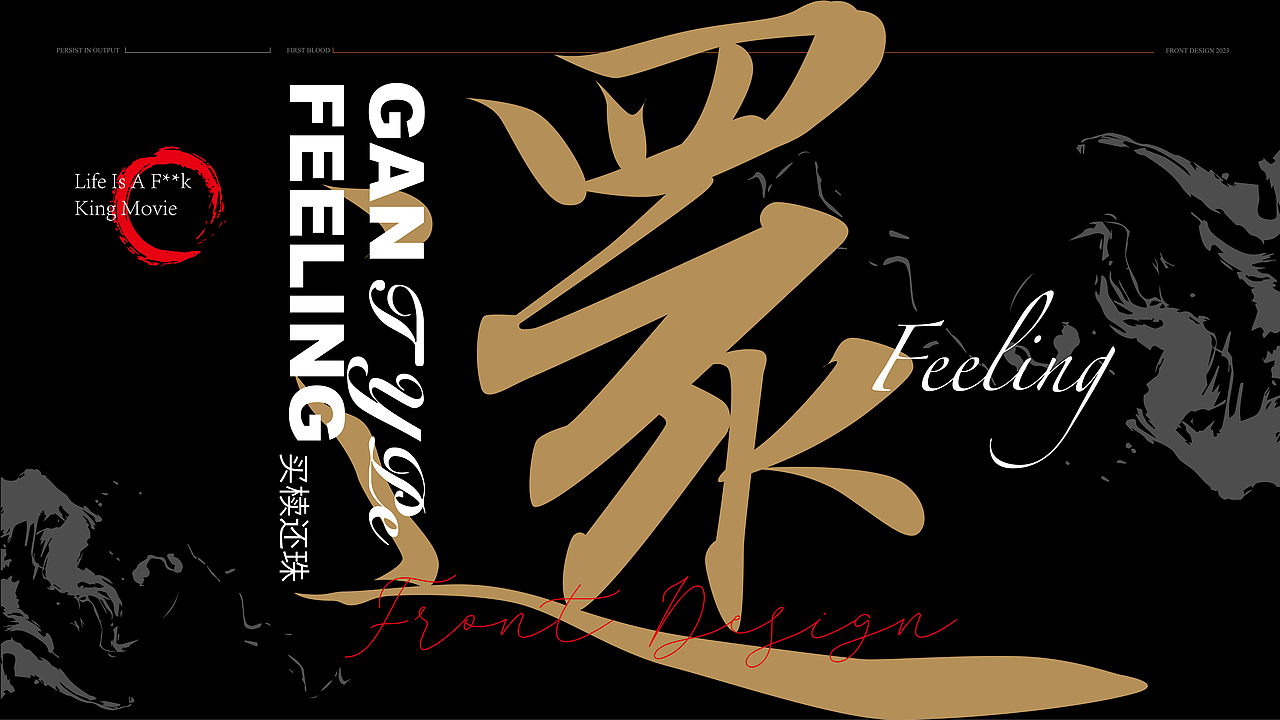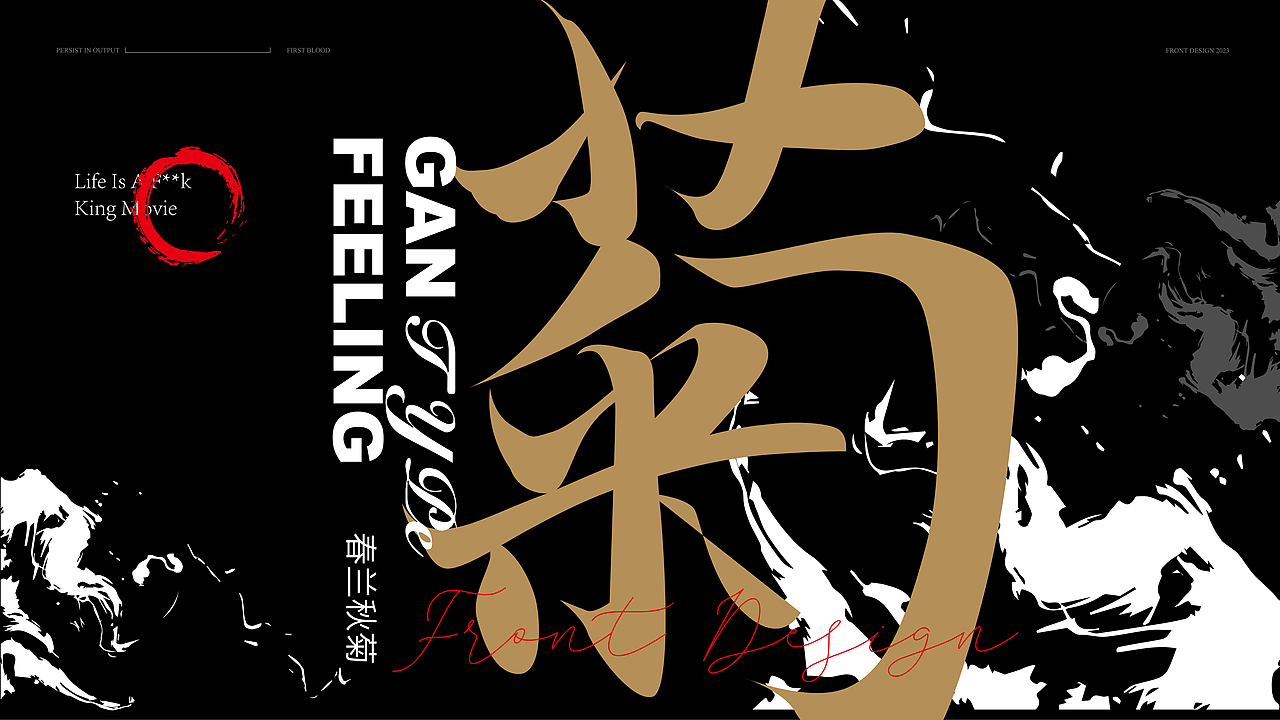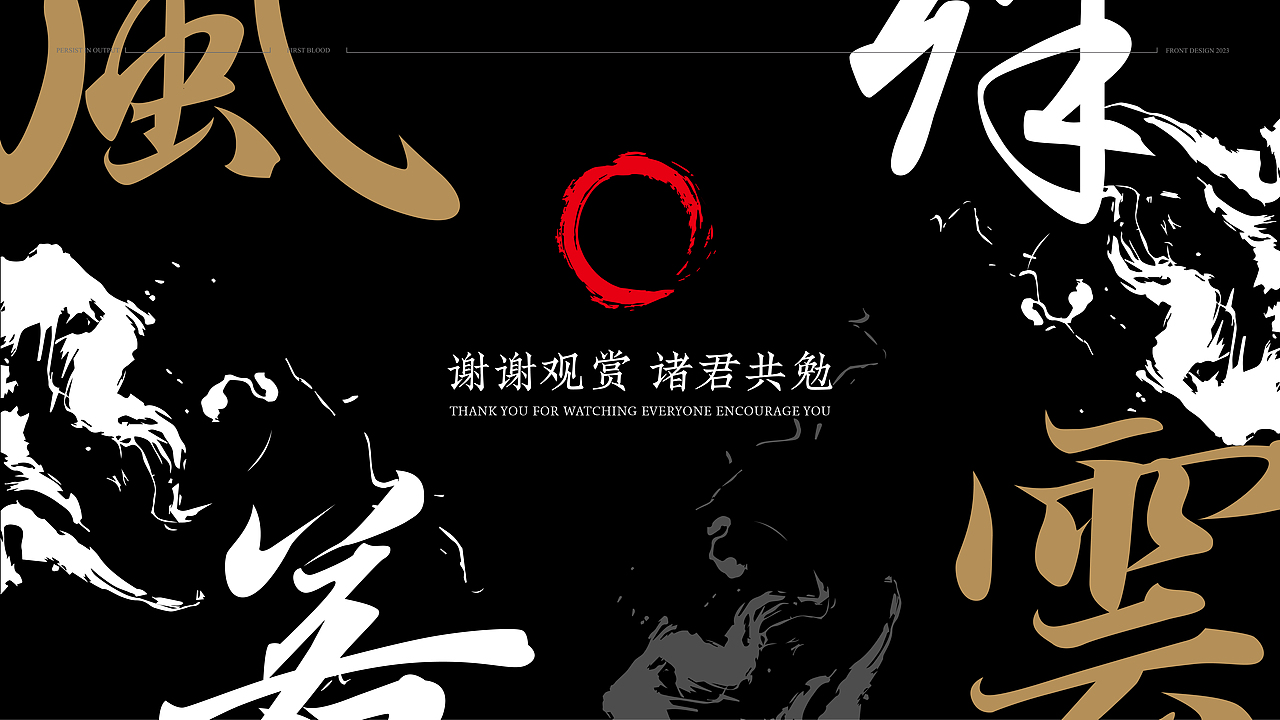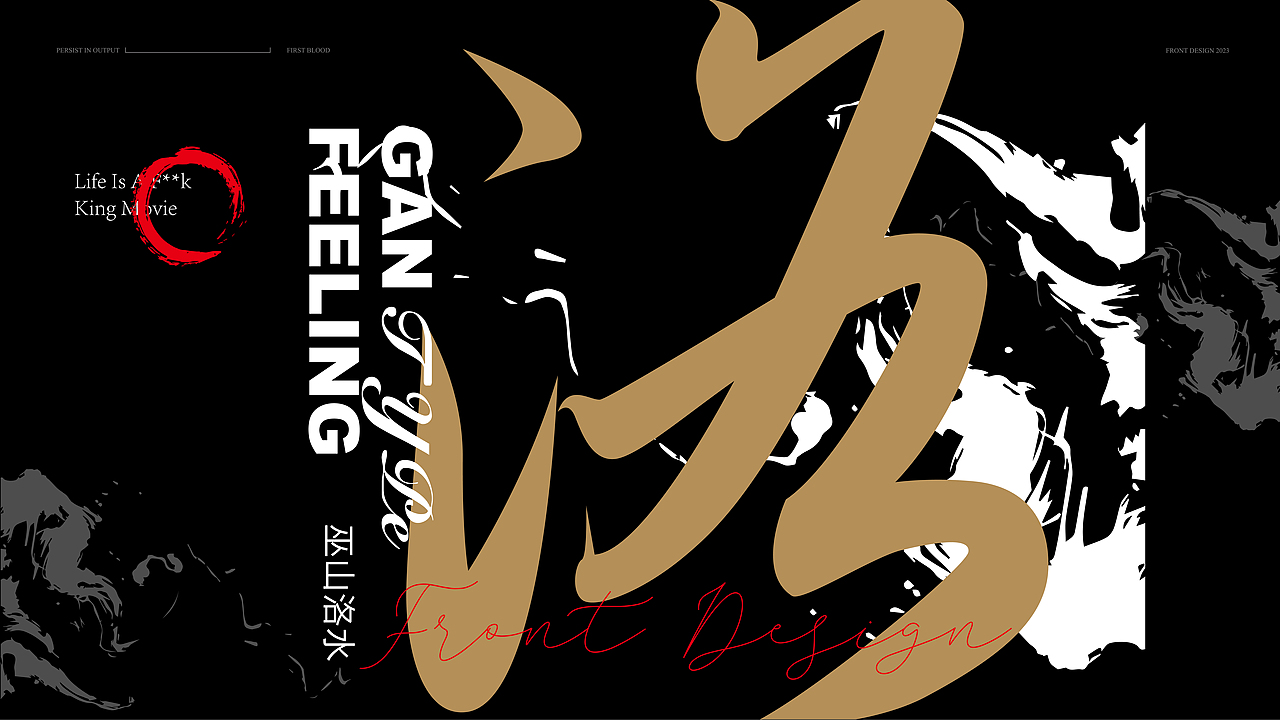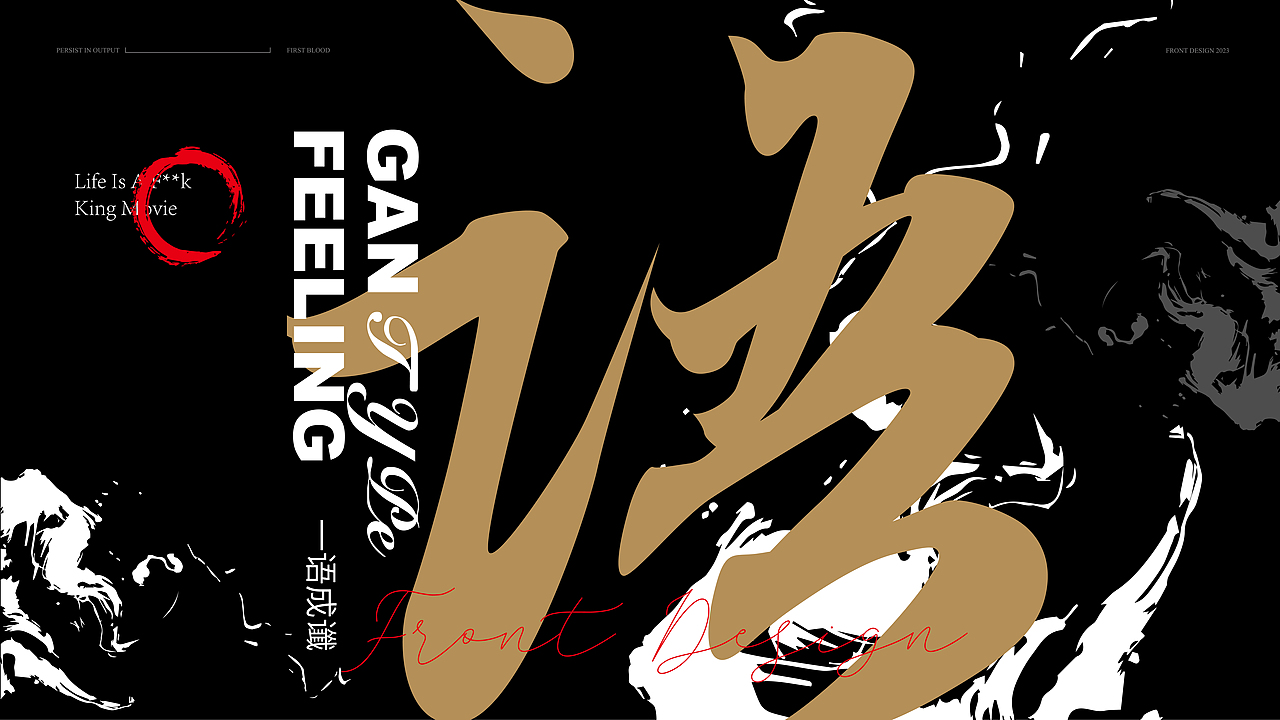
中国风&字体设计丨字体标志感官世界篇章
古字新说-手写字体设计/2023.08.01
古风字体/字体设计
黑体和柔美,粗犷与飞墨的碰撞,又会有什么样的火花。
What kind of sparks will there be when the collision between blackbody and femininity, rough flying ink, collides.